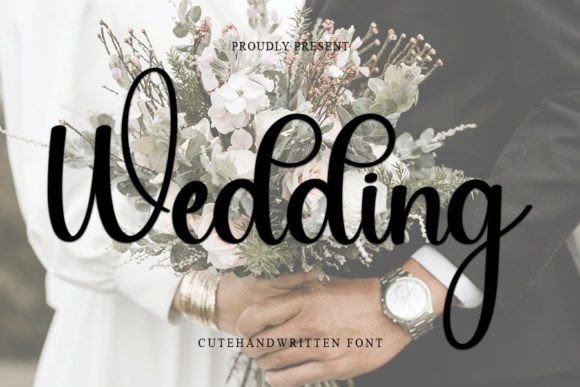
Wedding
Wedding : La police manuscrite qui fait battre les cœurs
Vous cherchez une typographie qui allie élégance et romantisme pour vos projets créatifs ? La police Wedding répond à toutes vos attentes. Inspirée d’une écriture manuscrite raffinée, elle se distingue par son style distinctif et intemporel, idéal pour les invitations, les cartes de vœux, les affiches de mariage ou tout autre support où la beauté du texte doit briller.
Pourquoi choisir la police Wedding ?
- Design élégant : chaque caractère possède une légère courbe qui rappelle la délicatesse d’une plume, apportant une touche sophistiquée à vos créations.
- Lisibilité optimale : malgré son aspect artistique, la police reste claire et facile à lire, même en petites tailles.
- Polyvalence : parfaite pour les invitations de mariage, les menus, les logos, les couvertures de livres et les projets de branding.
- Un style intemporel : grâce à son inspiration classique, la police ne se démode jamais, vous assurant un rendu élégant pour les années à venir.
4. Associez Wedding à une police plus neutre (ex. : Lato, Open Sans) pour créer un contraste visuel élégant.
Idées de créations avec la police Wedding
- Cartes d’invitation personnalisées pour un mariage chic.
- Menus gastronomiques raffinés pour un dîner de gala.
- Logotypes de marques de luxe ou de boutiques de papeterie.
- Couvertures de livres de poésie ou d’albums photo.
- Affiches d’événements culturels (concerts, expositions).
En résumé, Wedding est la police manuscrite qui transforme chaque texte en une œuvre d’art délicate et mémorable. Laissez‑vous séduire par son charme intemporel et créez des designs spectaculaires qui captivent l’œil et le cœur de votre audience.